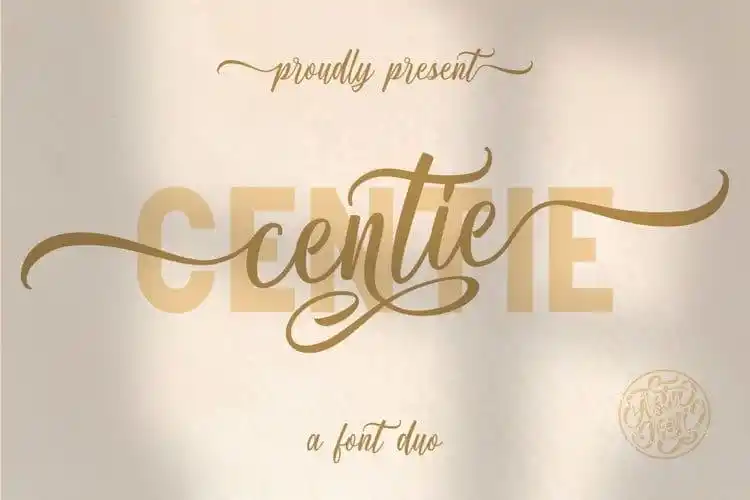
Centie Calligraphy Font Duo – Download Grátis
Centie Calligraphy Font Duo é uma fonte elegante que oferece a combinação perfeita entre simplicidade e sofisticação. Perfeito para aqueles que buscam um equilíbrio harmonioso entre modernidade e feminilidade, esta dupla de fóruns foi criada pelo designer Astageni utilizando um tipo serifado em par com uma tipografia sans-serif. O resultado é uma fonte de alta qualidade, capaz de enriquecer trabalhos gráficos variados sem comprometer sua legibilidade. Seu design limpo e sensual permite que os textos sejam leves e elegantes, enquanto o sinergismo entre serifas e linhas retas cria um contraponto atraente. Centie Calligraphy Font Duo é uma escolha inteligente para qualquer designer em busca de uma fonte versátil e moderna. Adicione esta dupla de fóruns aos seus projetos futuros e veja como ela torna tudo mais vivaz e atraente.